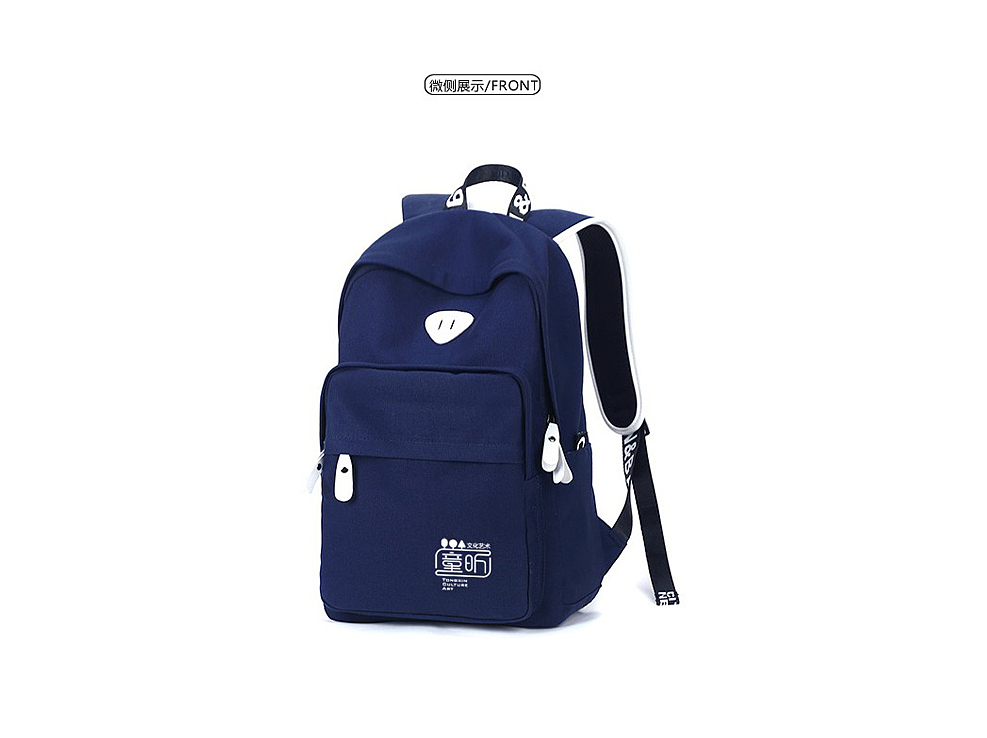
一日一标 004 JIANDESIGN
一周依然带来七个标志,有这周完成的,也有存货。
本周有尝试新的手法,也有比较满意的。
1. PartTime----------- 汽车修理零部件网站标志,P与一个扳手。简洁大气,完美
2.童昕-----------------儿童教育品牌,字体设计为主体。上面的三棵小树,三人行,必有电灯泡,哦,不对,必有我师。而且三在中西方的文化里面都 是一个包罗万象的数字。
3.艾克森起点-----------A&N,太阳,成长之门。
4.原本陶社----------方案一,纂书的笔画,以及增加了艺术描边。方案二:简约现代,干净利落。
5熊猫蛋糕----------可爱熊猫,眼睛&耳朵足以识别。
6叶飘然------------客户是专注于养生,以及传统文化的传播。之前是其他的方向,后经风水师指点,龙有利于调和整个气场。龙&阴阳。
7洛阳大叔---------使用笔触拼接而成,所幸客户比较满意。(可下载笔触)
PartTime----------- 汽车修理零部件网站标志,P与一个扳手。简洁大气,完美
儿童教育品牌,字体设计为主体。上面的三棵小树,三人行,必有电灯泡,哦,不对,必有我师。而且三在中西方的文化里面都 是一个包罗万象的数字。
A&N,太阳,成长之门。
纂书的笔画,以及增加了艺术描边。
简约现代,干净利落。
可爱熊猫,眼睛&耳朵足以识别。
客户是专注于养生,以及传统文化的传播。之前是其他的方向,后经风水师指点,龙有利于调和整个气场。龙&阴阳。
使用笔触拼接而成,所幸客户比较满意。(可下载笔触)